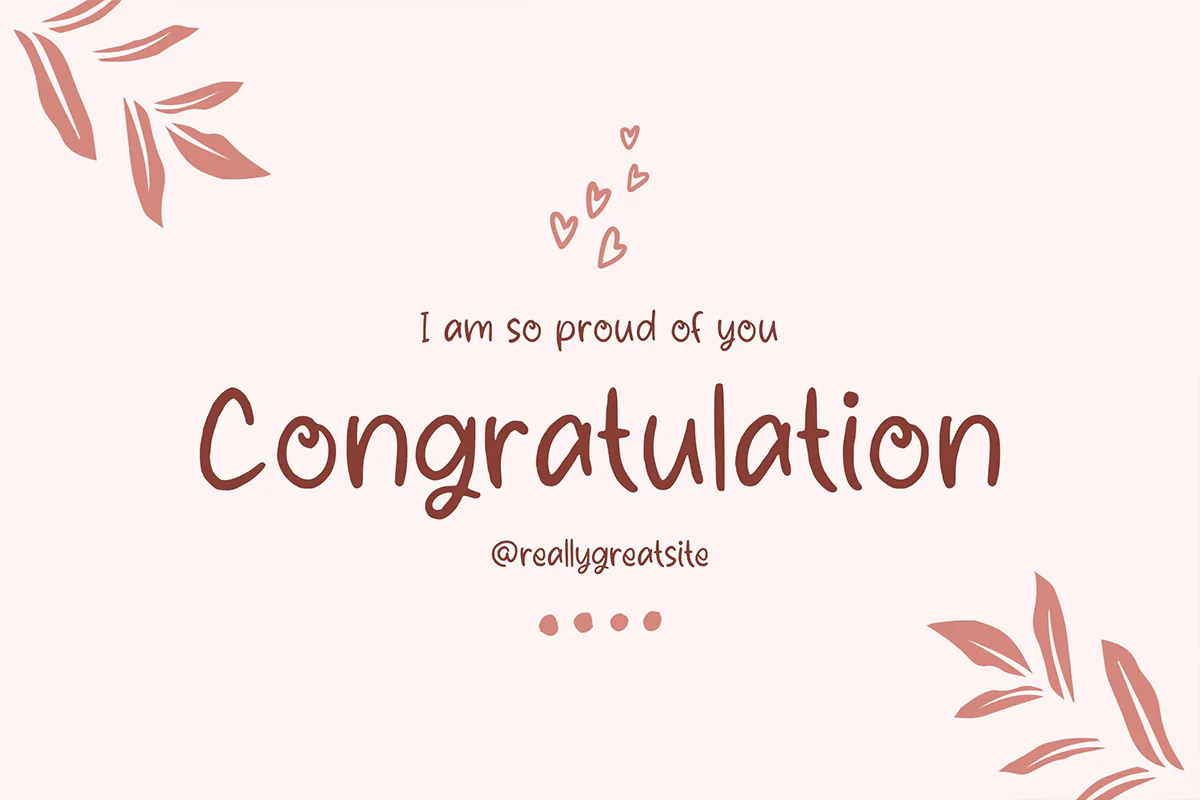
فونت دستنویس Natlycalie
فونت دستنویس انگلیسی
فونت دستنویس Natlycalie یک قلم فوق العاده زیبای انگلیسی است که مناسب برای استفاده در طرح و پروژههای گرافیکی مختلف همچون طراحی پوستر، کارت تبریک، بسته بندی محصولات، لوازم التحریر، کارت ویزیت و … میباشد.